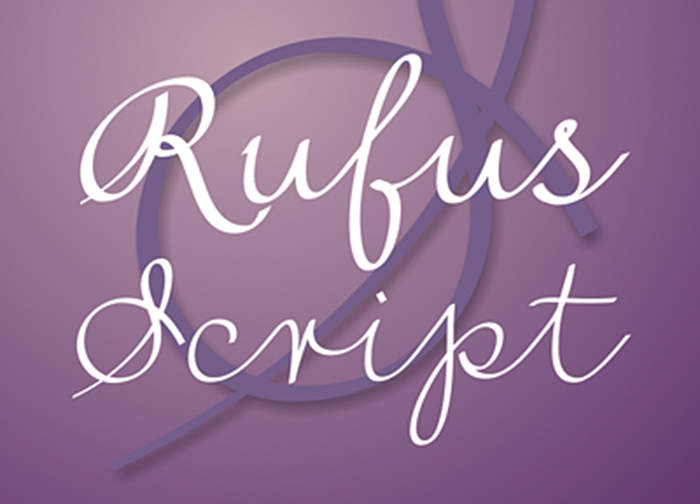
Aqui está uma descrição envolvente para a página de download da fonte Rufus Script Font: Introduzimos a Rufus Script Font! Desenhada pelo próprio Rufus e compartilhada por Paweł Burgiel, esta é uma fonte script conectada inspirada no método Palmer de escrita comercial (o lindo estilo de correspondência comercial do final do século XIX para o início do XX). A família Rufus Script oferece cinco pesos e vem com alternativas contextualizadas carregadas automaticamente. Seu conjunto de caracteres contém mais de 500 caracteres por fonte, fornecendo suporte para uma ampla variedade de idiomas baseados em latim. Inclui figuras proporcionais e tabulares, ornamentos e símbolos recicláveis populares usados nas embalagens. Esta fonte é excelente para aplicações variadas como embalagem de produto, capas de livros, desenho de posters, edições e cartões de agradecimento. Ela é particularmente adequada para longas inscrições graças à sua estrutura formal e às pequenas irregularidades que simulam a mão não completamente treinada. A Rufus Script é uma fonte perfeita tanto para profissionais quanto para entusiastas, oferecendo flexibilidade em muitas aplicações visuais de design gráfico. Ela traz um toque único e sofisticado às suas criações, sem dúvida tornando qualquer trabalho em que for usá-la mais atraente e inovador.